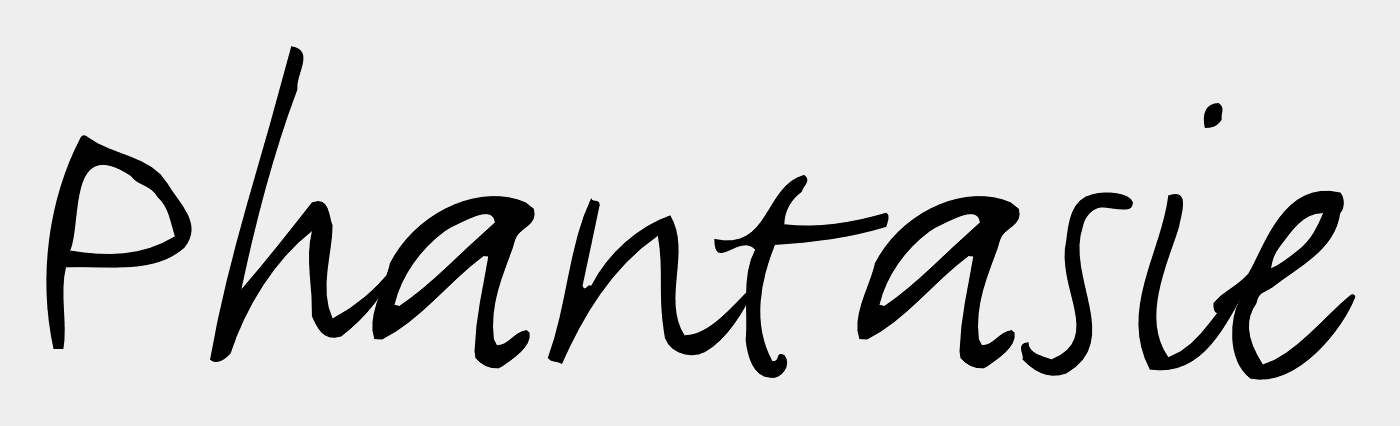
Handschrift-Schriftart als Illustration in Buch "Schreiben ist Gold"
kann mir bitte jemand helfen und mir sagen, wie diese Schriftart heißt. Sie wird in dem Buch "Schreiben ist Gold" von Eva-Maria Altenmöller in Illustrationen eingesetzt und ich dachte zunächst, es wäre eine Handschrift. Aber die Buchstaben sind absolut gleichmäßig und daher denke ich, es könnte ein Font sein. Ich habe eine Bekannte in England, die mit einer Feder fast genauso schreibt.
Ich kenne diese spezielle Schrift zwar nicht, aber die beiden identischen »a« lassen vermuten, dass es sich sehr wahrscheinlich um einen digitalen Font handelt. Hast Du schon mal unsere »10 Tricks« zur Schriftidentifikation ausprobiert?
Davon abgesehen sei mir eine kleine Nebenbemerkung erlaubt: Wenn das gezeigte Wort mit einer Feder geschrieben wurde, dann hat die aber ordentlich auf dem Papier gekratzt!
Jetzt kann ich mich mit diesem Font beschäftigen. Habe schon herausgefunden, dass er mal als "Spaßschrift" begonnen hat.
Mir gefällt er halt, da er mich an meine Freundin in England erinnert, die in Reading bei Michael TwymanTypografie studiert hat... ;-)